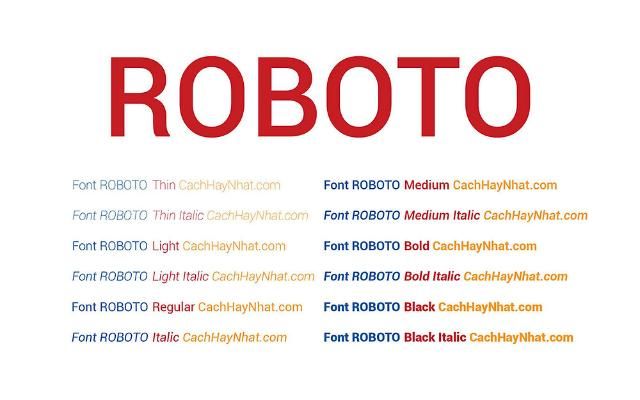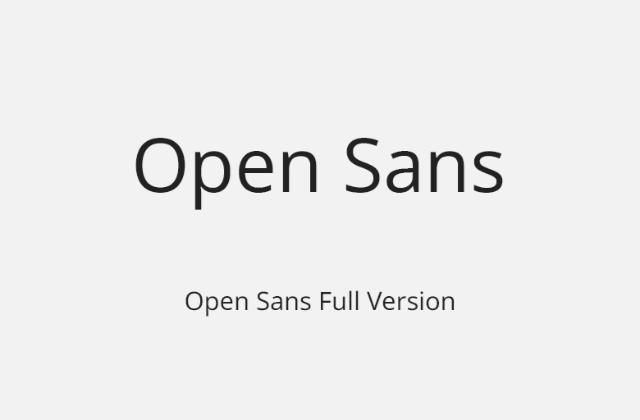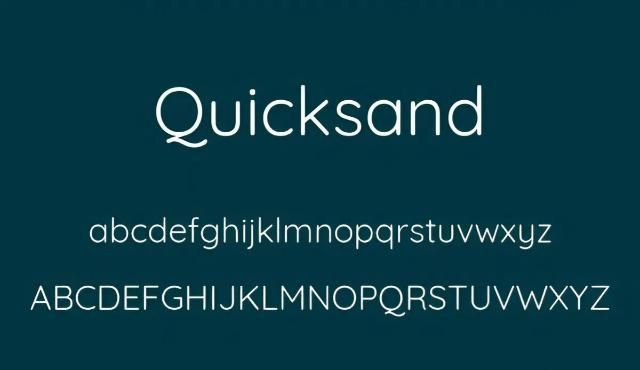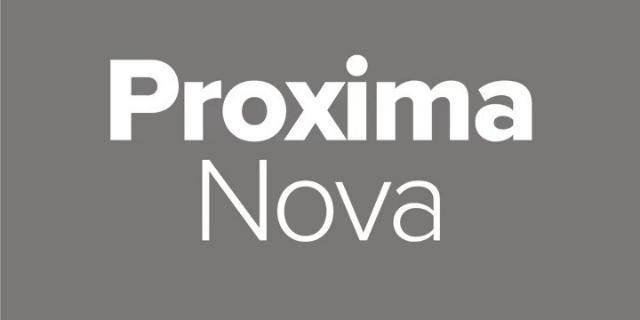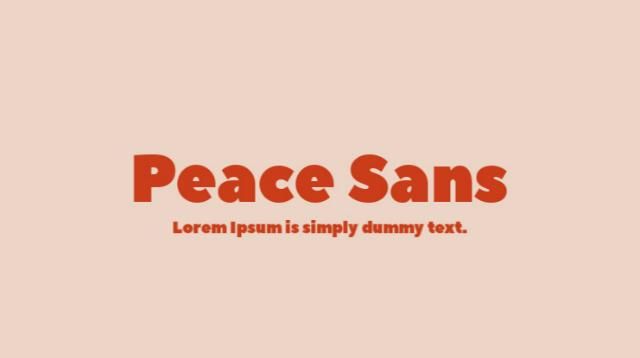
Sự tối giản, đường nét dứt khoát và khả năng hiển thị rõ ràng trên nhiều thiết bị là những yếu tố giúp font chữ không chân trở thành lựa chọn phổ biến trong thiết kế hiện đại. Nhóm font này mang lại cảm giác chuyên nghiệp, thanh lịch và dễ đọc, phù hợp với cả thiết kế website, logo, banner, poster lẫn các ấn phẩm truyền thông số.
Nếu bạn muốn dự án thiết kế của mình có diện mạo hiện đại, gọn gàng và dễ tạo thiện cảm với người xem, font chữ không chân là lựa chọn rất đáng cân nhắc. Trong bài viết này, chúng tôi sẽ tổng hợp những font chữ không chân Việt hóa đẹp, dễ dùng và được ưa chuộng nhất hiện nay để bạn có thể tải về và ứng dụng ngay cho thiết kế của mình.
Font chữ không chân là gì?
Font chữ không chân (còn gọi là Sans Serif) là nhóm font không có các nét gạch nhỏ ở phần đầu hoặc cuối ký tự. Khác với font chữ có chân Serif, Sans Serif sở hữu đường nét đơn giản, gọn gàng và dễ nhìn hơn trên các thiết bị kỹ thuật số. Dòng font này bắt đầu xuất hiện từ thế kỷ 19 và trở nên phổ biến mạnh mẽ trong thế kỷ 20, đặc biệt trong thiết kế hiện đại, giao diện website và các ấn phẩm truyền thông online.
Điểm nổi bật của font chữ không chân là cảm giác trẻ trung, rõ ràng và linh hoạt. Các ký tự được thiết kế tối giản, ít chi tiết thừa nên giúp người đọc dễ tiếp nhận nội dung, nhất là khi hiển thị trên màn hình máy tính, điện thoại hoặc máy tính bảng. Vì vậy, Sans Serif thường được sử dụng trong thiết kế website, slide thuyết trình, banner, poster, logo, brochure và nhiều ấn phẩm quảng cáo khác.
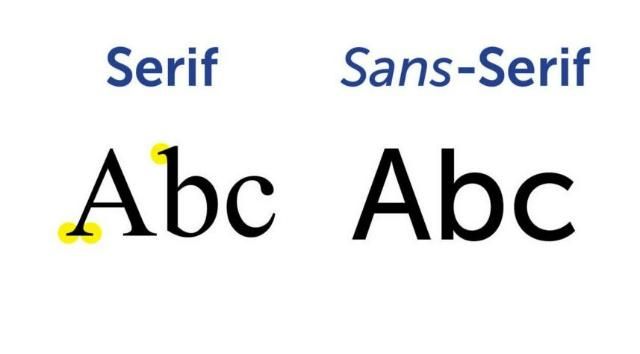
Font chữ Sans Serif có nhiều ưu điểm đáng chú ý:
- Dễ đọc, ít gây rối mắt: Do không có phần chân chữ nên các ký tự trông thoáng, rõ và dễ nhận diện hơn.
- Phong cách hiện đại: Sans Serif mang cảm giác trẻ trung, tối giản, phù hợp với các thiết kế công nghệ, sáng tạo, giáo dục, thương mại điện tử và truyền thông số.
- Ứng dụng linh hoạt: Có thể dùng trong thiết kế logo, giao diện website, banner, poster, brochure, bao bì, slide trình chiếu và nội dung mạng xã hội.
- Tối ưu cho môi trường online: Font chữ không chân hiển thị tốt trên nhiều kích thước màn hình, giúp cải thiện trải nghiệm đọc và tính thẩm mỹ của thiết kế.
Tuy nhiên, Sans Serif cũng có một số hạn chế. Nếu sử dụng ở kích thước quá nhỏ hoặc chọn font có nét quá mảnh, chữ có thể bị khó đọc, đặc biệt trên màn hình chất lượng thấp. Ngoài ra, nhóm font này thường mang phong cách hiện đại nên không phải lúc nào cũng phù hợp với các thiết kế cần cảm giác sang trọng, cổ điển hoặc trang trọng như một số font Serif.
Trong thực tế, font chữ không chân được ứng dụng rộng rãi trong nhiều lĩnh vực. Với thiết kế website, Sans Serif là lựa chọn phổ biến vì giúp nội dung hiển thị rõ ràng, dễ đọc và thân thiện với người dùng. Với thiết kế nhận diện thương hiệu, nhóm font này thường được dùng cho logo, banner, brochure, bao bì và ấn phẩm quảng cáo nhằm tạo cảm giác chuyên nghiệp, hiện đại và dễ ghi nhớ.
Top 20+ font chữ không chân đẹp nhất và được sử dụng phổ biến hiện nay
Font chữ không chân, hay còn gọi là Sans Serif, là nhóm font không có các nét gạch nhỏ ở đầu hoặc cuối ký tự. Đặc điểm nổi bật của loại font này là đường nét rõ ràng, tối giản, dễ đọc và phù hợp với các thiết kế hiện đại.
Nhờ khả năng hiển thị tốt trên màn hình, font chữ không chân được sử dụng nhiều trong thiết kế website, ứng dụng di động, logo, banner, poster, slide thuyết trình, nhận diện thương hiệu và các ấn phẩm truyền thông số.
Dưới đây là những font chữ không chân đẹp, phổ biến và dễ ứng dụng hiện nay:
1. Helvetica Now
Helvetica Now là phiên bản hiện đại của dòng Helvetica nổi tiếng, mang phong cách tối giản, rõ ràng và chuyên nghiệp. Font này có độ cân bằng tốt, dễ đọc và phù hợp với nhiều loại bố cục thiết kế.
Ứng dụng: Helvetica Now thường được dùng trong thiết kế logo, nhận diện thương hiệu, website, poster, banner, hồ sơ doanh nghiệp và các ấn phẩm cần cảm giác cao cấp, tinh gọn.
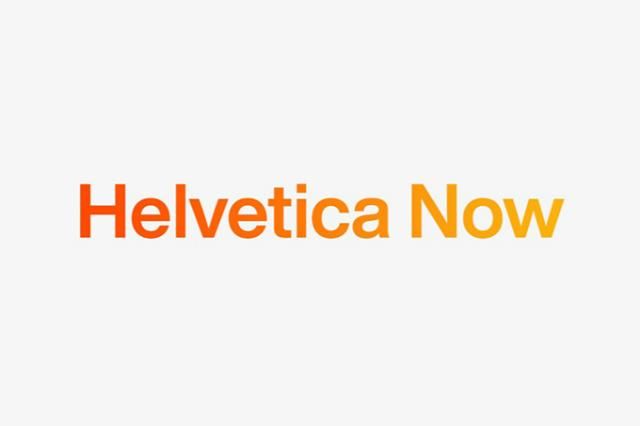
2. Futura
Futura là font chữ không chân mang phong cách hình học, được xây dựng từ các đường nét gọn gàng, cân đối và hiện đại. Font này tạo cảm giác thanh lịch, sáng tạo và có hơi hướng tương lai.
Ứng dụng: Futura phù hợp với thiết kế logo, bao bì sản phẩm, poster, thương hiệu thời trang, công nghệ, kiến trúc và các dự án cần hình ảnh hiện đại, khác biệt.
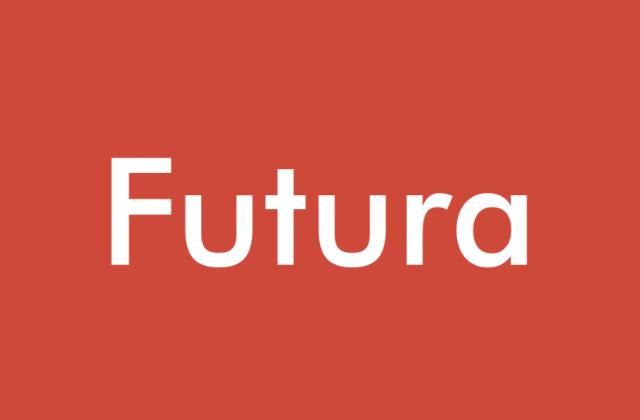
3. Arial
Arial là một trong những font Sans Serif quen thuộc nhất, có khả năng hiển thị rõ ràng và dễ đọc trên nhiều nền tảng. Font này mang phong cách đơn giản, trung tính và dễ sử dụng.
Ứng dụng: Arial thường được dùng trong văn bản, tài liệu văn phòng, website, email, slide, tiêu đề phụ và các thiết kế cần sự rõ ràng, phổ thông.
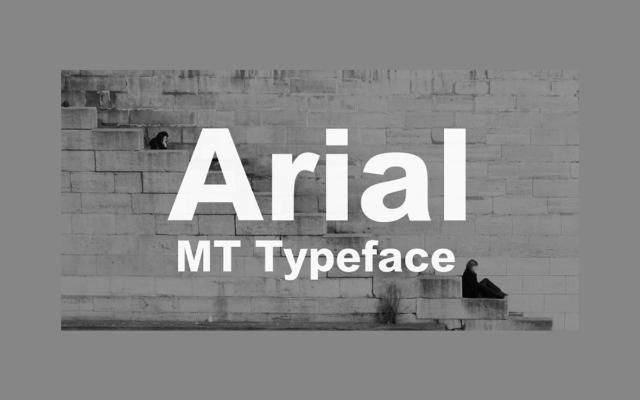
4. Calibri
Calibri là font chữ không chân có đường nét mềm mại, hiện đại và dễ nhìn. Đây từng là font mặc định phổ biến trong Microsoft Office, nên rất quen thuộc với người dùng.
Ứng dụng: Calibri phù hợp với tài liệu Word, Excel, PowerPoint, báo cáo, slide thuyết trình, nội dung website và các ấn phẩm cần sự gọn gàng, dễ đọc.
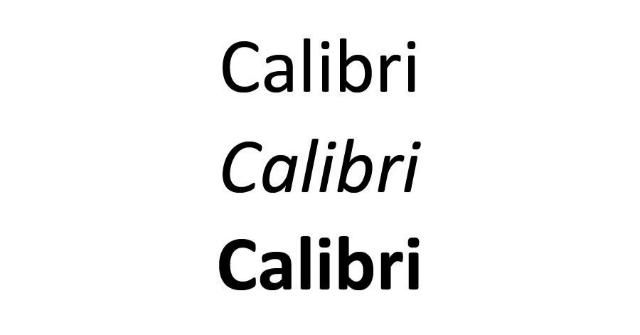
Trên đây là tổng hợp 25 font chữ không chân đẹp, hiện đại và được sử dụng phổ biến hiện nay. Mỗi font đều có đặc điểm riêng về kiểu dáng, độ dễ đọc và khả năng ứng dụng trong thiết kế website, logo, banner, poster, slide thuyết trình hoặc nhận diện thương hiệu. Bạn có thể tham khảo từng mẫu để chọn font phù hợp với phong cách thiết kế và mục đích sử dụng của mình.